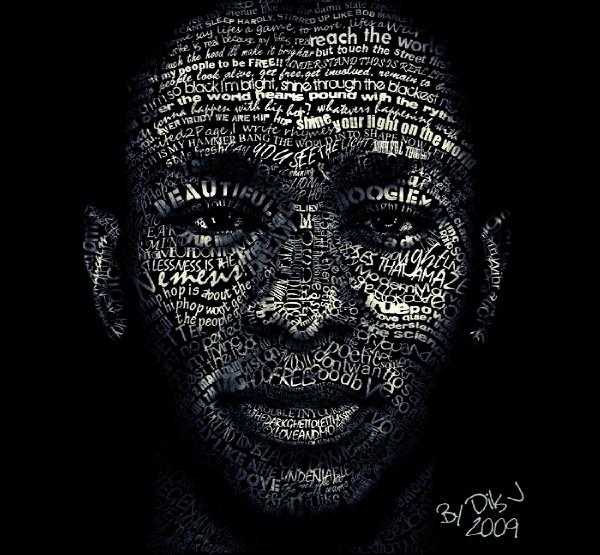
El arte de los retratos con tipografía
Estoy seguro de que la mayoría de nosotros ha oído hablar de esta memorable frase que dice "Una imagen vale más que mil palabras". Pero hoy quiero mostrar algo diferente, un híbrido de ambas (imagen y palabra).
A veces, incluso la cuestión más complicada puede ser simplificada y expresarla en una sola imagen, que por otra parte puede ser increíble. En esta ocasión voy a comentar dos artículos que están hablando del mismo tema, la tipografía, pero afortunadamente en la actualidad, el uso de los tipos de letra ya no se limita solamente al texto de los artículos o medios de comunicación.
Se puede rizar el rizo, mediante hacer una imagen (retrato) con el texto , también conocido como el arte de texto. Consiste en lugar de utilizar los pinceles y un lienzo, en esta ocasión nos vamos al mundo virtual, y nos aprovechamos de la magia que existe detrás de los equipos y software de edición como Photoshop o Illustrator. En el primer artículo, titulado The beauty of typographic portraits , de Creativityden, podemos ver algunos ejemplos de varias formas y técnicas para crear un retrato tipográfico, que no se limita solamente a plasmar personas, también puede ser un anuncio social, los créditos de una película, vídeos musicales, y muchas más cosas.
En este otro artículo, es una recopilado que muestra hasta donde llega la increíble imaginación de algunos artistas realmente creativos. El segundo artículo se trata de 28 Excellent Examples Of Typography Portraits publicado en Hongkiat. Una muestra con un enfoque muy especial a las ilustraciones de retrato, con una mezcla de imágenes y la tipografía, que se utiliza para dar forma a los retratos. Es increíble cómo la manipulación de los tipos de letras, estilos y tamaños, pueden formar una obra de arte con cierto significado interior.